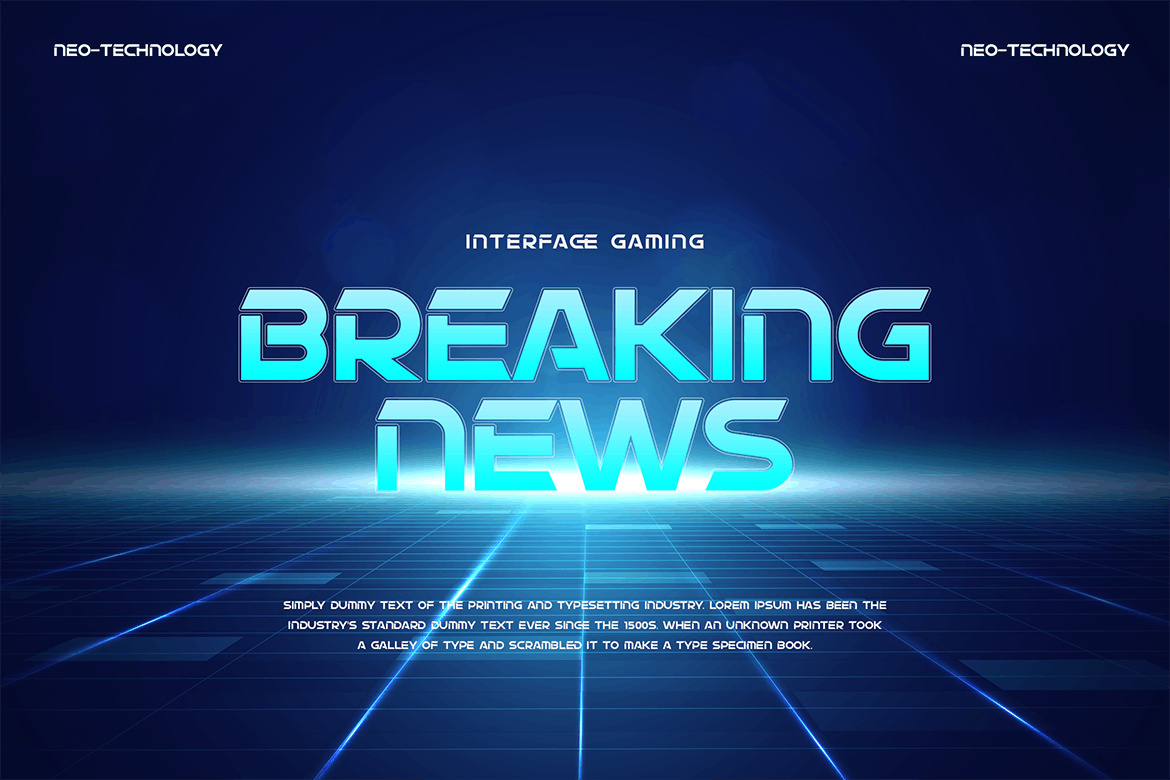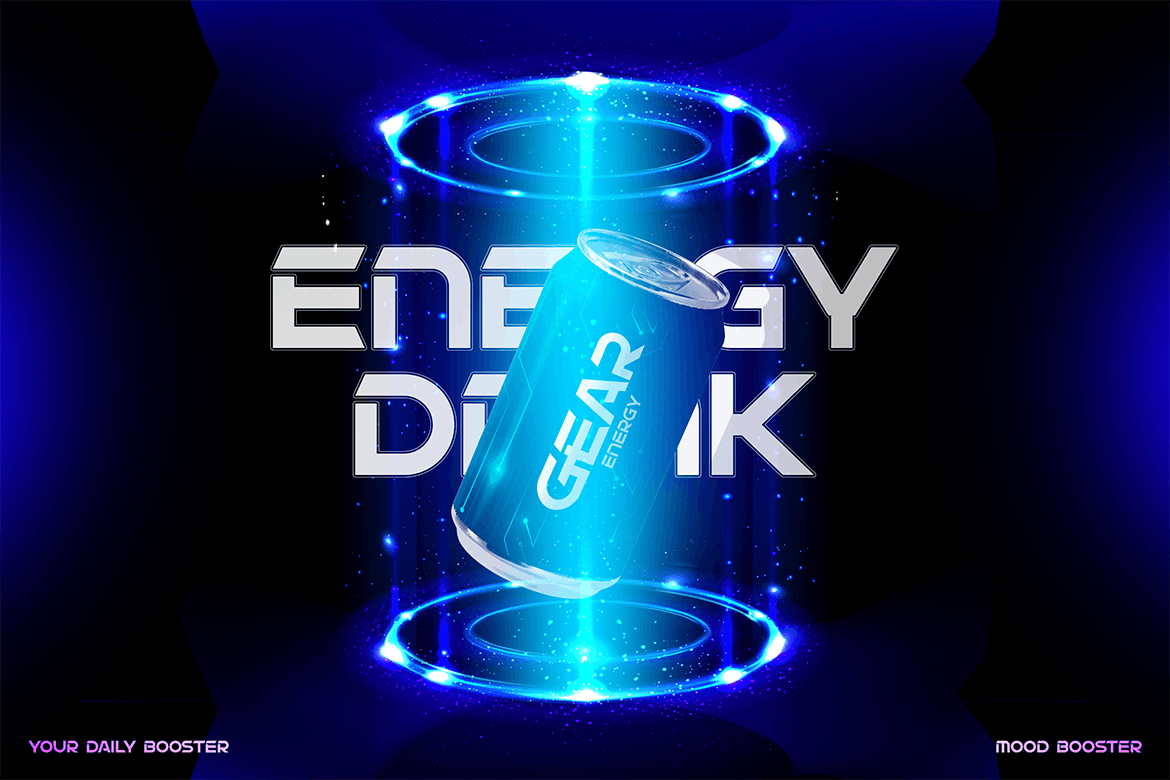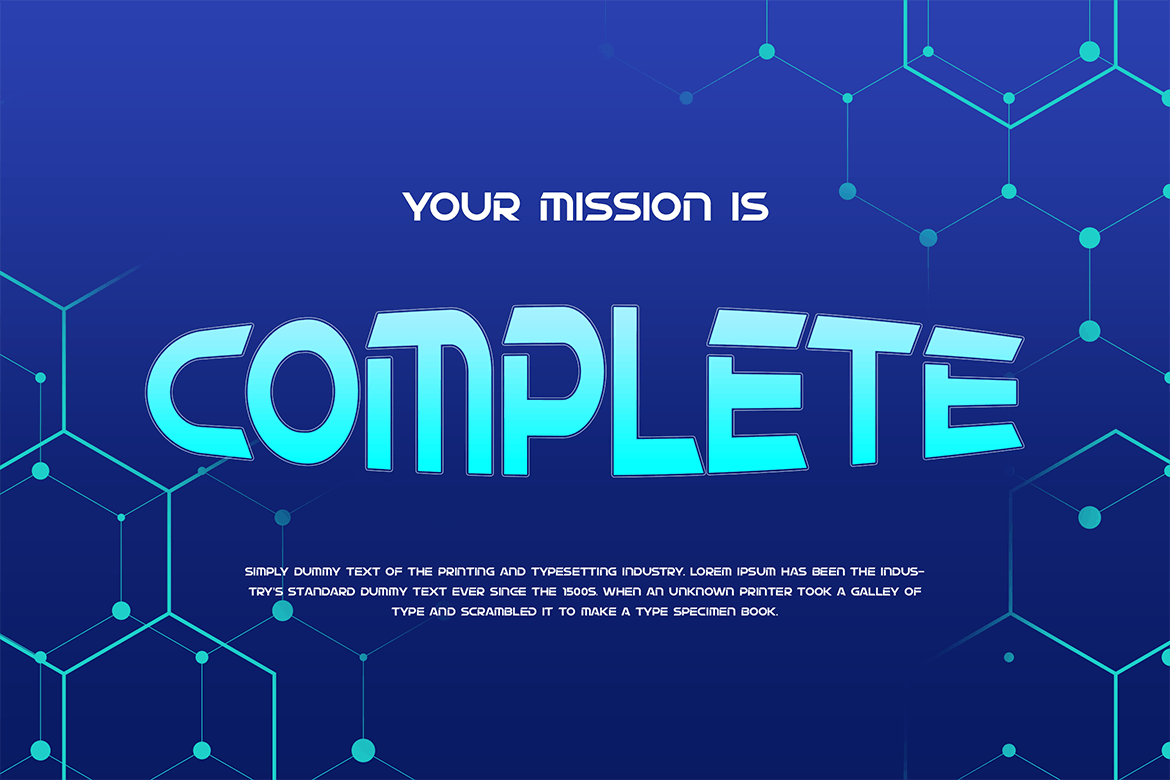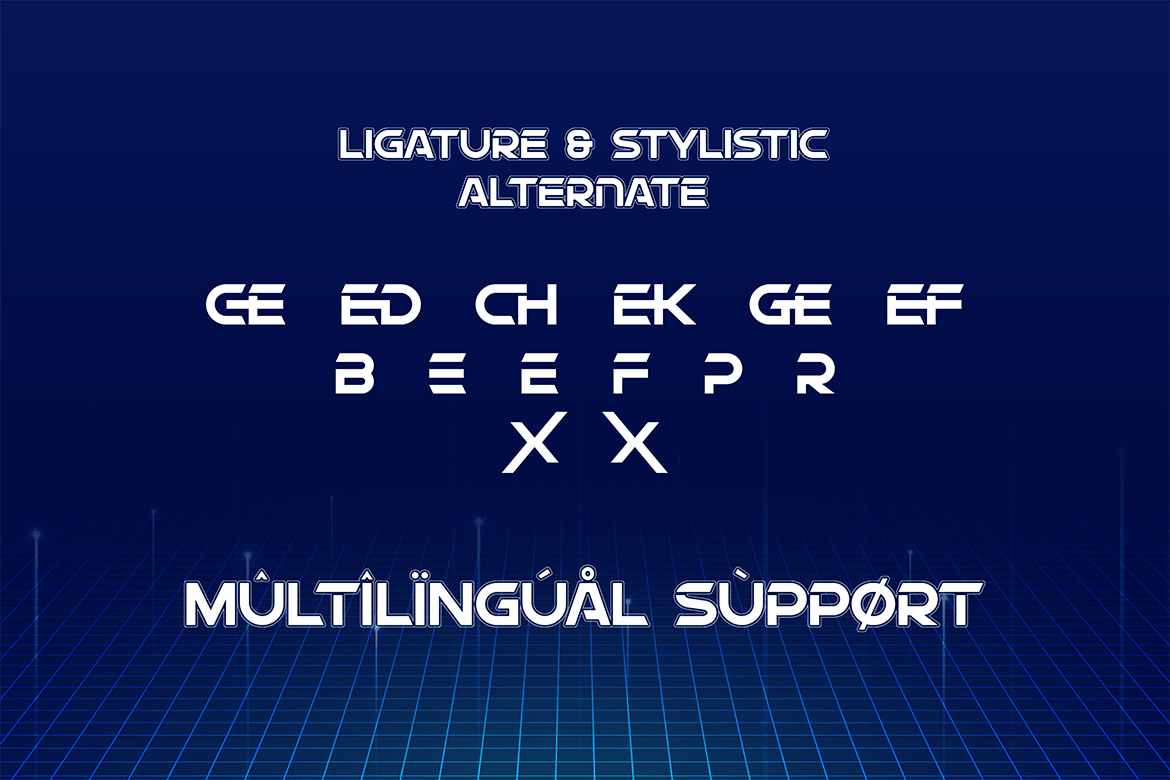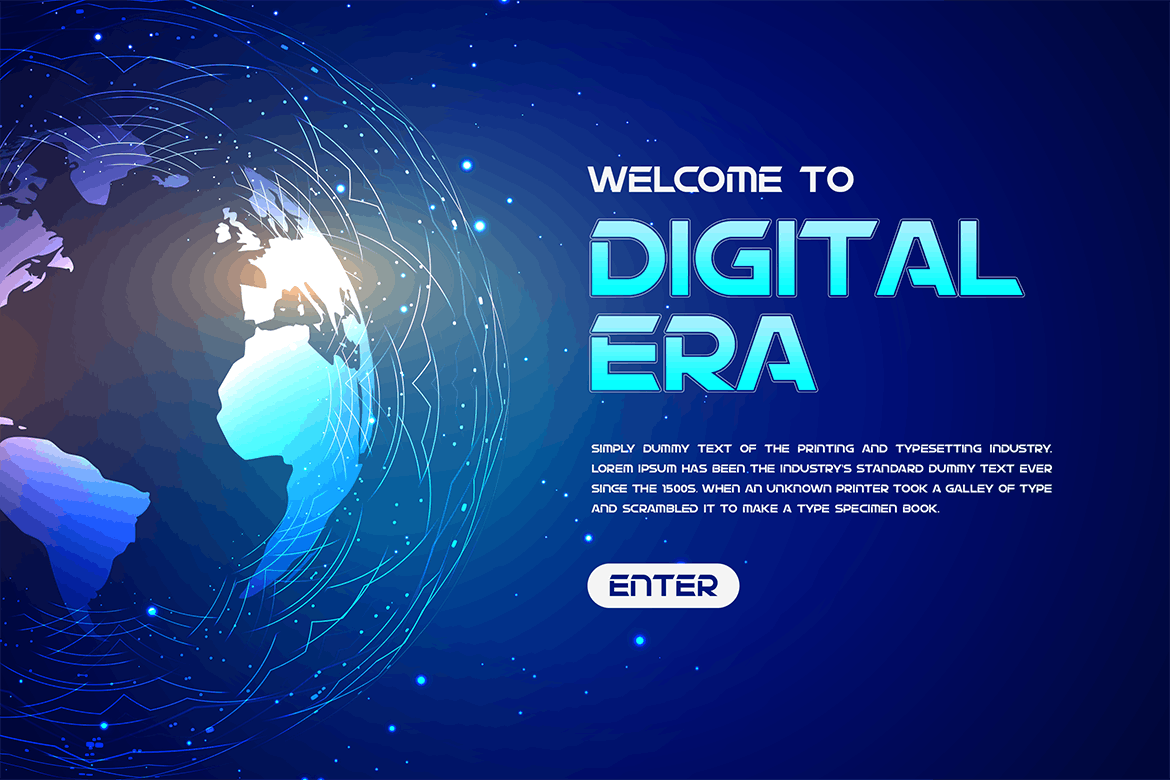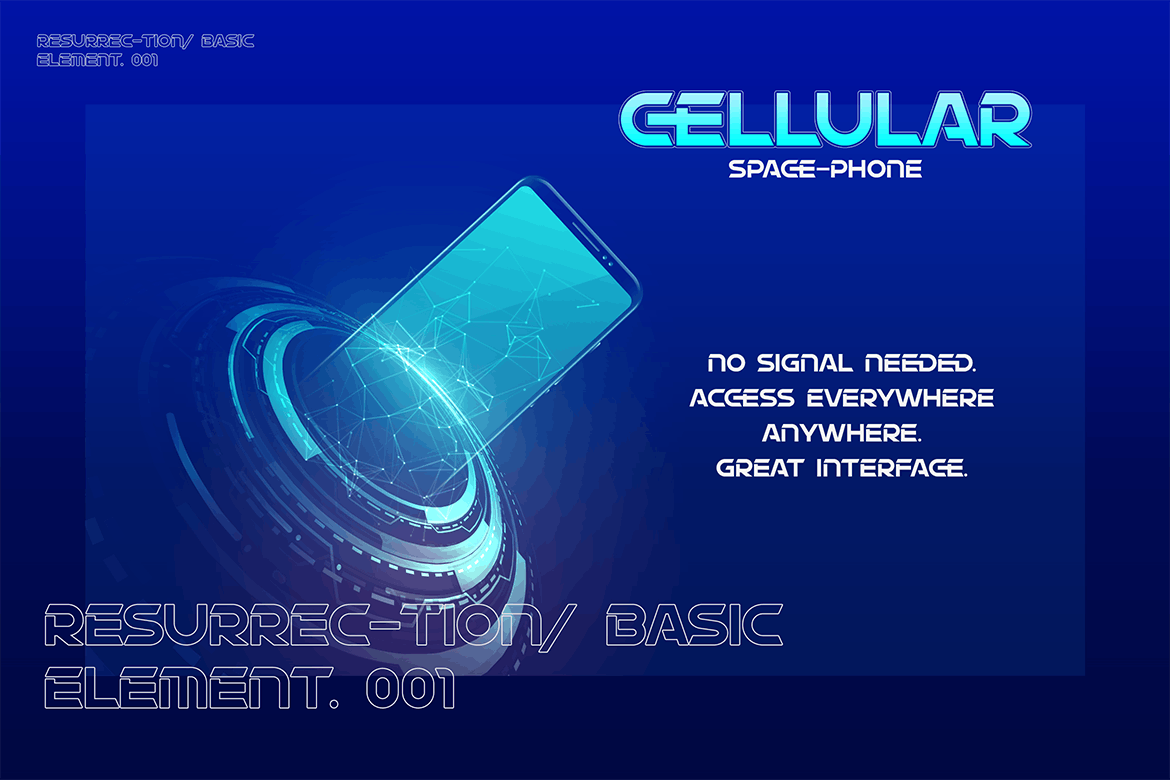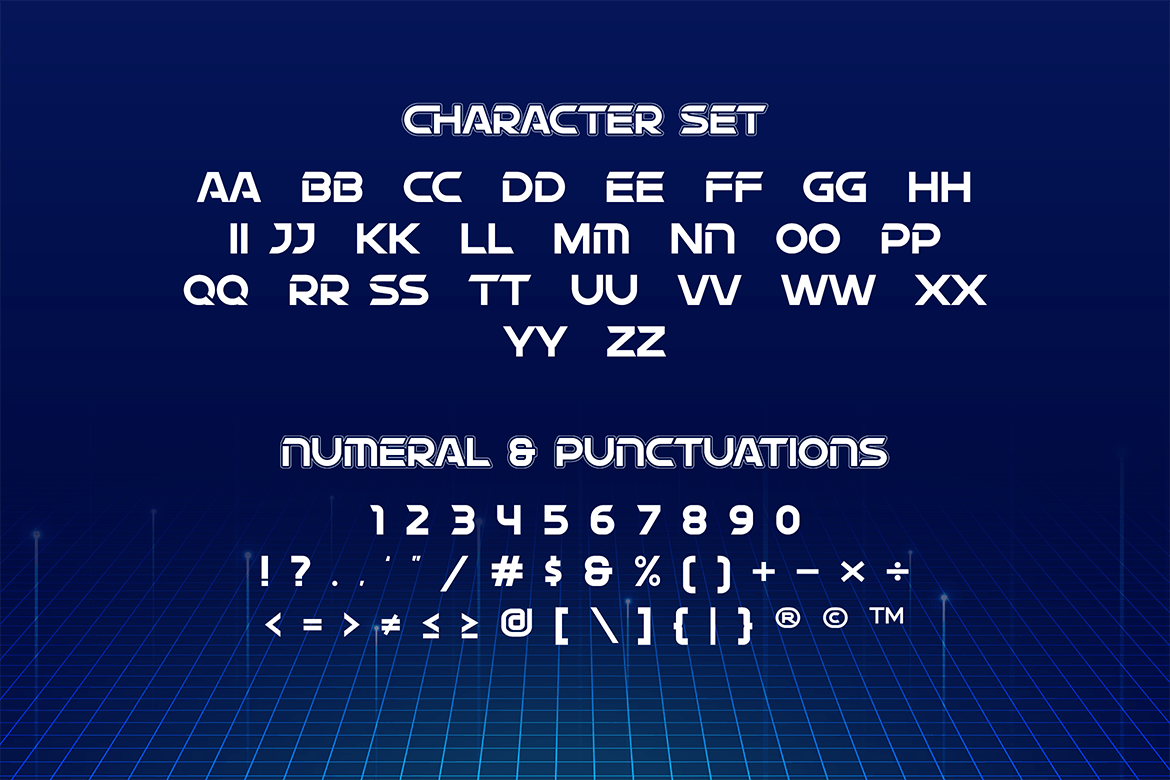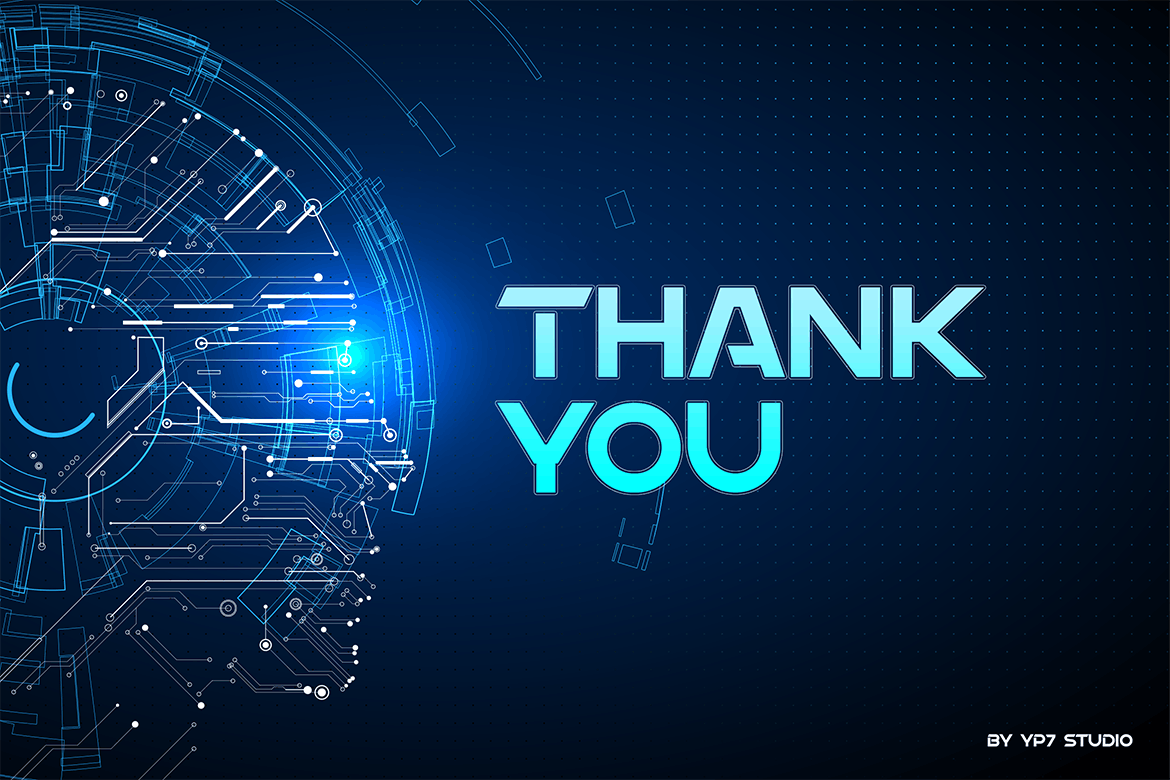
دانلود فونت مدرن Nedgen برای طراحی
Nedgen Modern Display Font
فونت Nedgen با طراحی مدرن، بهترین گزینه برای پروژه‌های گرافیکی شماست.
فونت مدرن Nedgen یک انتخاب عالی برای طراحان است که به دنبال یک فونت منحصر به فرد و جذاب هستند. این فونت با طراحی زیبا و کاربرپسند خود، مناسب برای استفاده در پروژه‌های مختلف گرافیکی می‌باشد.
• حروف بزرگ
• حروف کوچک
• اعداد و نشانه‌گذاری